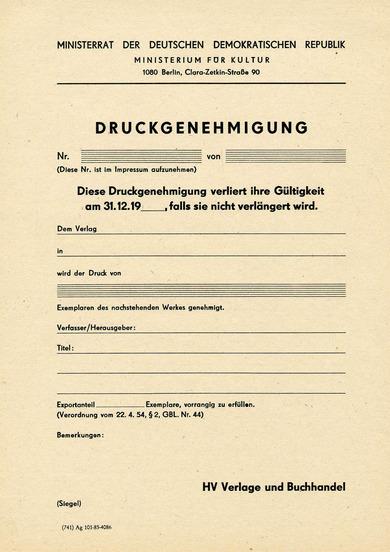
Nach der Lektüre der Wiki stelle ich betrübt fest, daß ich bisher, und zu meinem Schaden, nichts, gar nichts, über Leipzig wußte 😞
Du wusstest doch aber, dass etliche Schriftgießereien in Leipzig ansässig waren oder?
Schelter & Giesecke, Breitkopf & Härtel, Ludwig Wagner, Julius Klinkhardt, Gottfried Böttger, Heinrich Hoffmeister, C. Tauchnitz, C. Kloberg, A. Numrich, F. A. Brockhaus …
In diesem Zusammenhang das Antragsformular:
Und selbst dieses Formular unterlag der Genehmigungspflicht, wie man an derm Zeichen der erteilten Genehmigung unten links sehen kann.  Ich habe noch einmal nachgesehen, alle meine DDR-Bücher tragen auf der Impressumseite solch ein Kürzel
Gestern in einem WP-Artikel habe ich wohl zu viele Wörter
fremdsprachigen Ursprungs erwartet und mich gefragt, was Ber-
garten wohl ist, dabei ging's da sogar um (schottische) Berge und
ihre speziellen Klassifizierungssysteme, aber so ist das wohl,
wenn man das nebenher macht, während man gerade den
TV-Beitrag zu diesem Thema schaut ...
Ach, und müde war ich gestern abend auch und wohl immer noch nicht ganz wach, um den kniffligen Wortfaden zu finden ... *flöt* ;-)
und man auf das i verzichtete.
Das hatte man dann fürs »Gebirge« noch übrig.
Du wusstest doch aber, dass etliche Schriftgießereien in Leipzig ansässig waren
Jaja, aber ich meinte die Stadt als solche. Von den meisten Metropolen habe ichein geistiges Bild, entweder weil ich da war, oder Bilder gesehen oder darüber gelesen habe. Leipzig ist ein schwarzes Loch. Ich kann Dir keine einzige Sehenswürdigkeit oder Lokalität nennen. Das werde ich heute Abend soweit möglich berichtigen.
Sehenswürdigkeit
Vergiss bloß die Hörenswürdigkeiten nicht:
Jetzt fehlt noch die 3. Dimension für andere Übergänge ... ;-)
Von den meisten Metropolen habe ichein geistiges Bild, entweder weil ich da war, oder Bilder gesehen oder darüber gelesen habe. Leipzig ist ein schwarzes Loch.
Dann könnte eine Straßenbahnfahrt vielleicht helfen:
Vielen, vielen Dank, Peter; das ist der absolute Hammer! Ich habe mir das Video jetzt mal von vorn bis hinten angekuckt und bin von einigen Sachen überrascht.
1. Das annähernde Monopol der lateinischen Schrift im Straßenbild. Ich habe jetzt wirklich drauf geachtet, aber überhaupt nur 2 Beispiele gebrochener Schrift gesehen: an 2 Fahrzeugen, die direkt hintereinander geparkt waren und mglw. sogar dasselbe Gewerbe beworben haben. Ansonsten hunderte Male lateinische Schrift. 1931 waren gebrochene Schriften also zumindest entlang dieser Straßenbahnroute fast (oder tatsächlich?) seltener als CJK oder Arabisch in vielen deutschen Innenstädten heute. Wahnſinn!
2. Wie dominant Asphalt damals schon war. Ich habe nur an einer Stelle mal länger Kopfsteinpflaster gesehen (und es war dort prima zu erkennen; am Film liegt das also nicht).
3. Wie luxuriös Ausbau und Taktung des Straßenbahnsystems waren. An den entgegenkommenden Bahnen sieht man, dass es einen Takt von wenigen Minuten gegeben haben muss. Und es ging zügig voran. Die Haltestellenabstände waren gering, aber die Bahn hielt an Haltestellen nur wenige Sekunden (sicher auch, weil keine Türen geöffnet und geschlossen werden mussten und die Fahrgäste eben schnell auf- und abspringen konnten).
4. Wie dunkel viele Fassaden waren. In der DDR haben wir ja immer gedacht, dass das nur bei uns so war, weil wir eben arm waren und Wandfarbe dekadent-unnötiger Luxus war. Aber 1931 herrschte ja Kapitalismus in Leipzig! (Klar, Weltwirtschaftskrise und so, aber die war noch gar nicht so lange im Gang, dass so schnell die ganzen Fassaden der bunten 20er verdreckt worden wären.)
5. Das war jetzt nicht so überraschend, aber interessant zu sehen war es allemal, wie wenig dominant der motorisierte Verkehr neben all den Fußgängern, Radfahrern, Handkarren und Pferdefuhrwerken war.
6. Die Seelenruhe der die Straße überquerenden Leipziger. Kaum einer scheint mal nach links oder rechts zu kucken. Die sich rapide nähernde Bahn beeindruckt auch niemanden. Alle schlendern einfach weiter, als seien sie allein auf der Straße.
Ach und noch was ganz merkwürdiges: praktisch immer, wenn eine Bahn entgegen kommt, fehlen immer allerletzten Moment, immer da, wo sich die Fahrer normalerweise grüßen würden, ein paar Frames. Was könnte es damit auf sich haben? Sollten die Fahrer heraus geschnitten werden? Wollte man Standbilder der entgegen kommenden Bahnen haben? (Ansonsten scheint der Film praktisch komplett ungeschnitten.)
Ich fand eigentlich, dass die Fahrer (damals nur Männer, oder? :-?) auffällig wenig geklingelt haben.
Die Originalaufnahme ist stumm; der Ton ist -- ausweislich der Videobeschreibung -- nachträglich hinzugefügt. Wahrscheinlich wurde die Kamera mit einer Handkurbel betrieben, was auch die leicht schwankende Gehgeschwindigkeit der Leute erklärt. Für den Elektromotor einer automatischen Filmkamera hätte auf der Straßenbahn auch wahrscheinlich die Stromversorgung gefehlt. Mit Tonfilm (Lichtton) wäre Handbetrieb dagegen nicht möglich: das leiert dann nämlich.